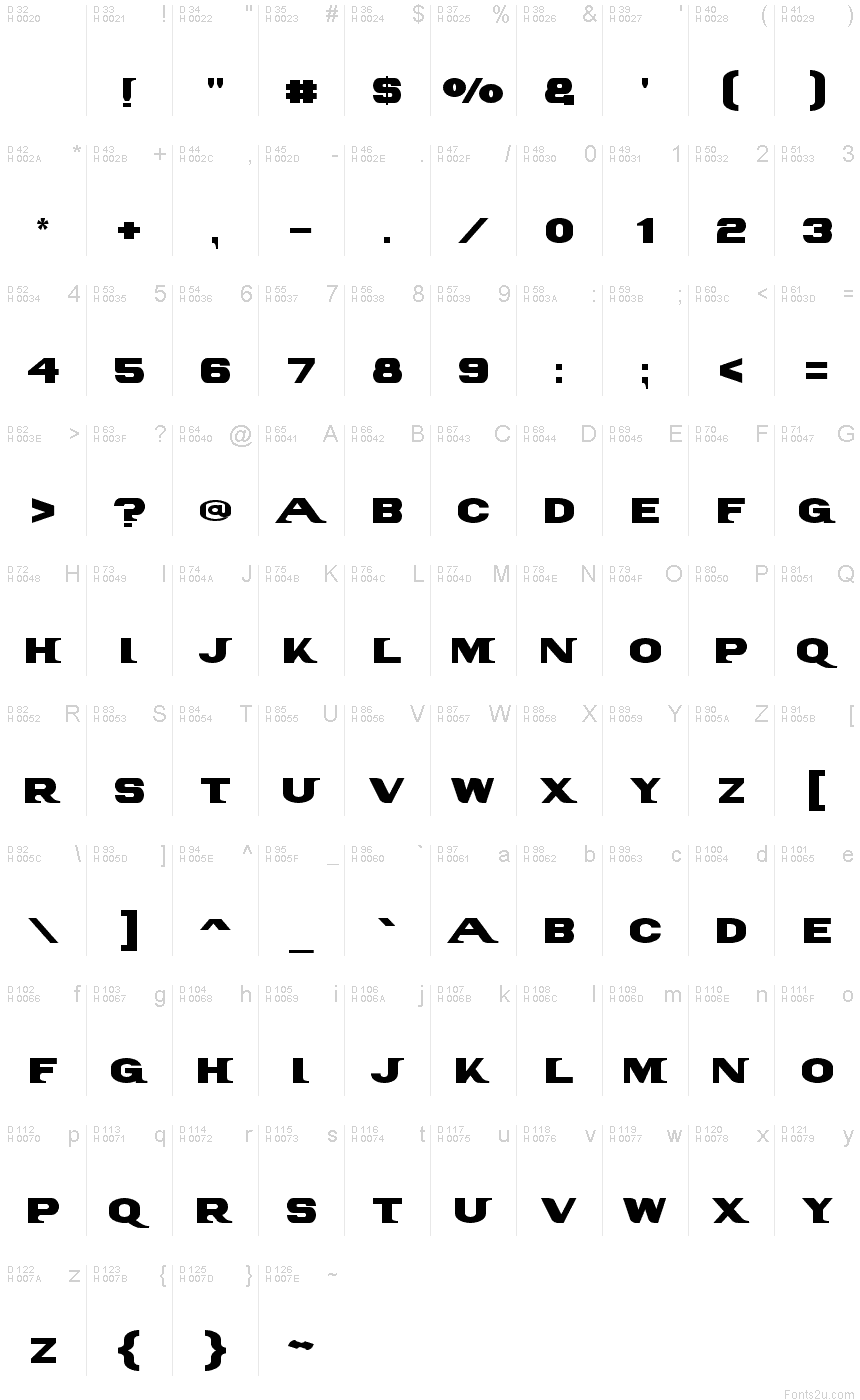
PanAm LogoText od GM to darmowy font typu display w stylu logo, charakteryzujący się odważną, geometryczną konstrukcją i ostrymi, trójkątnymi cięciami. Litery są ze sobą ściśle powiązane, a szerokie łuki i kanciaste łączenia nadają nazwie opływowy charakter w stylu lotniczych szyldów.
PanAm LogoText świetnie sprawdza się w brandingu, logotypach, plakatach, tytułach, opakowaniach i projektach w stylu retro, ponieważ jego język form został zaprojektowany z myślą o znaku graficznym, a nie o długich tekstach. Ten darmowy font pasuje również do oznakowań, etykiet i akcentów redakcyjnych, gdy potrzebujesz wyrazistego, symbolicznego znaku z wyraźnym lotniczym nawiązaniem.